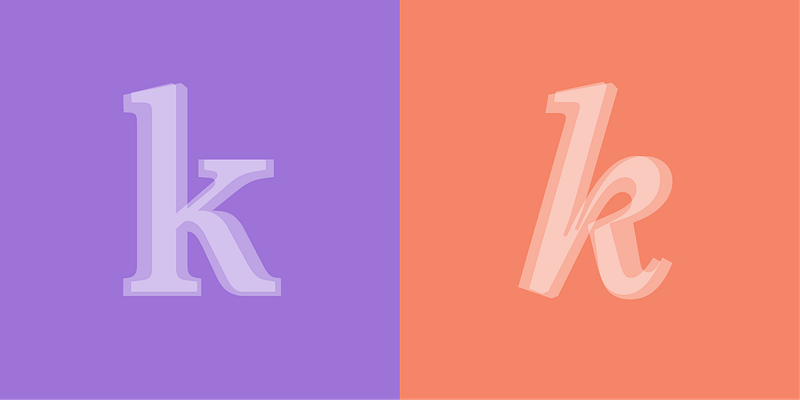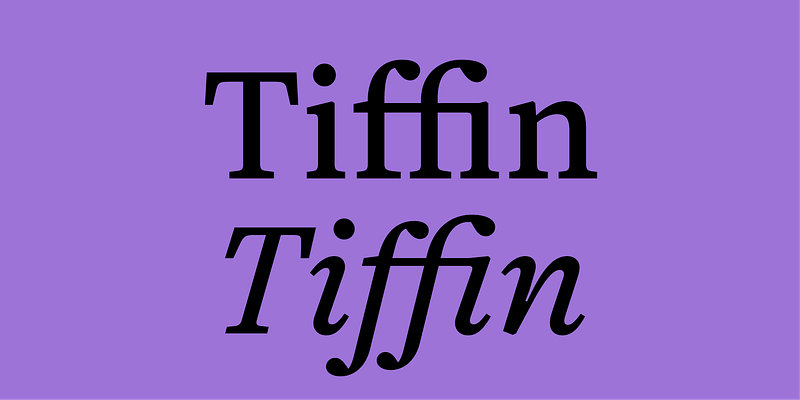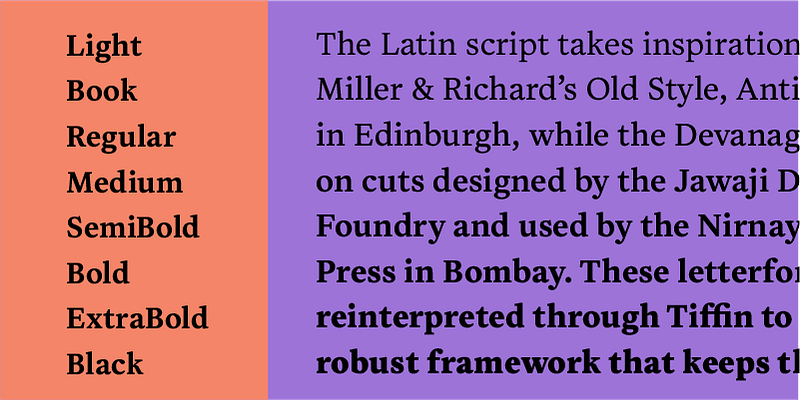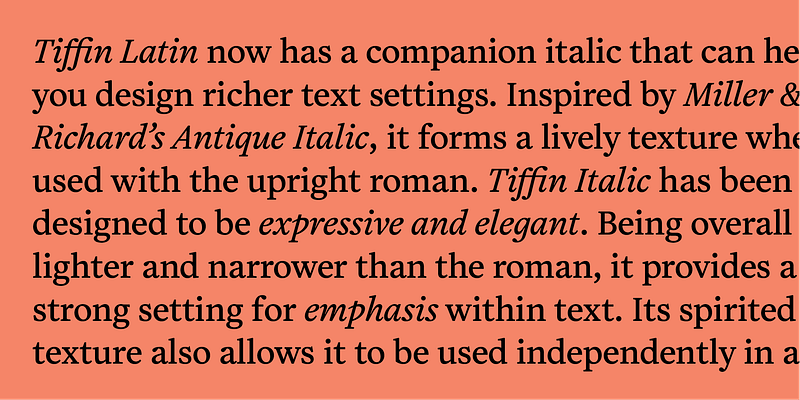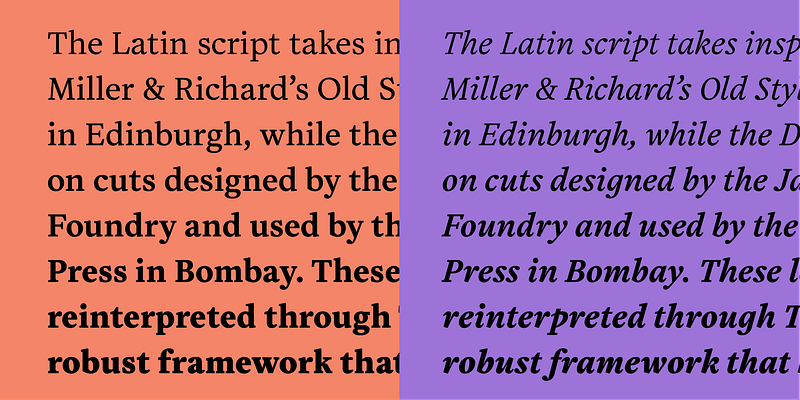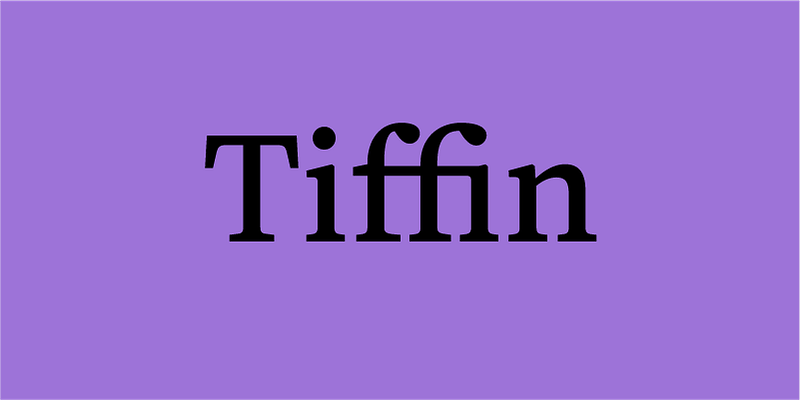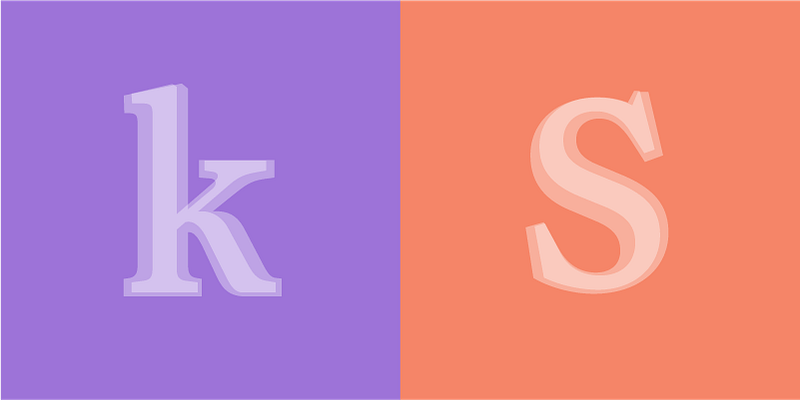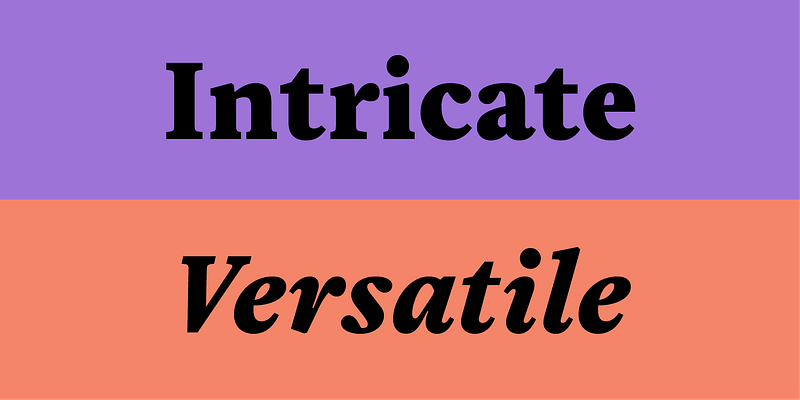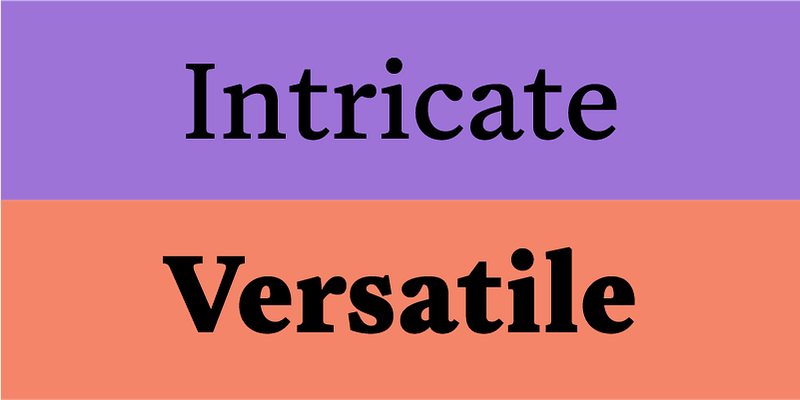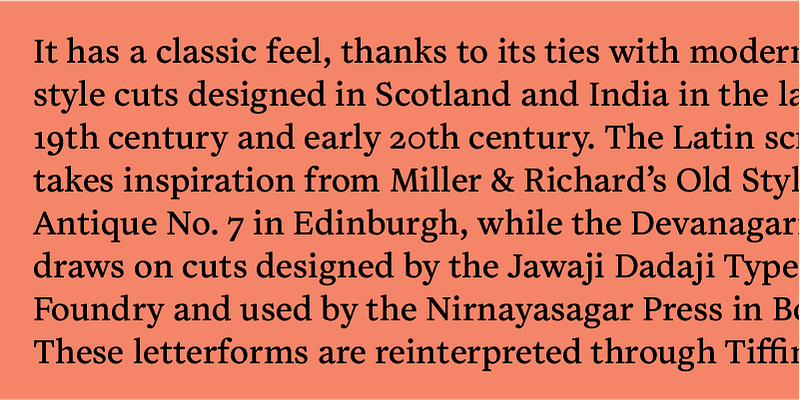
Tiffin は、スクリプトを個別にまたは一緒に設定するために使用できる多用途のラテン語および Devanagari 書体です。19 世紀後半から 20 世紀初頭にかけてスコットランドやインドでデザインされたモダンなオールドスタイルカットとのつながりにより、クラシックな雰囲気が漂います。
ラテン文字はエディンバラにある Miller & Richard のオールドスタイル、Antique No.7 からインスピレーションを得ており、Devanagari はJawaji Dadaji 活字フォントメーカーがデザインし、ボンベイの Nirnayasagar 印刷所で使用されているカットを参考にしている。これらの文字形式は Tiffin を通じて再解釈され、厳密に現代性を保つ堅牢なフレームワークを形成します。Tiffin の正確かつ慎重な設計により、2 つのスクリプトはその構造に忠実でありながらシームレスに連携して動作することができます。
Tiffin には思慮深さと誠実さがありますが、根底には遊び心があり、様々なテーマ、ジャンル、形式に柔軟に対応できます。ノーベル賞を受賞した小説を植字したり、ユートピアの未来に向けたマニフェストの草稿を作成したりするために使用します。
書記体系 : ラテン語、Devanagari
サポートされている言語: ヒンディー語、マラーティー語、ネパール語、マルワリ語、英語など。